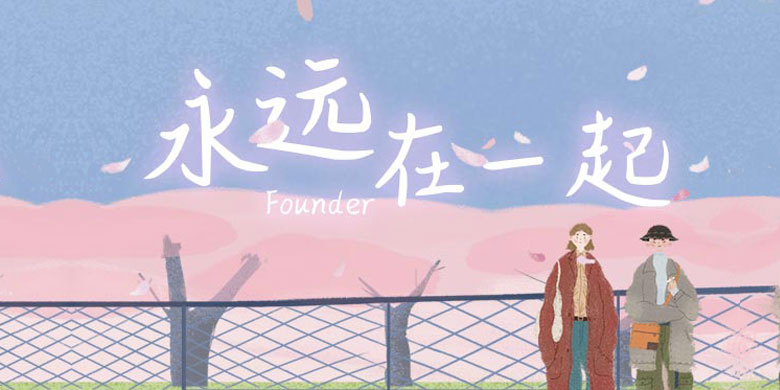
方正手迹-永远在一起
字体品牌: 方正手迹 设计师:刘晔 字体分类:创意书写 字体属性:精品字 字符集:大陆简体(GB2312-80) 发布时间: 2020
永远在一起这款字体字形偏扁,但中宫紧凑,线条浑厚,结构独具新意,让人回味。适用于现代诗歌、短文类的书刊、品牌广告和产品包装设计,以及社交网络的个性化用字。